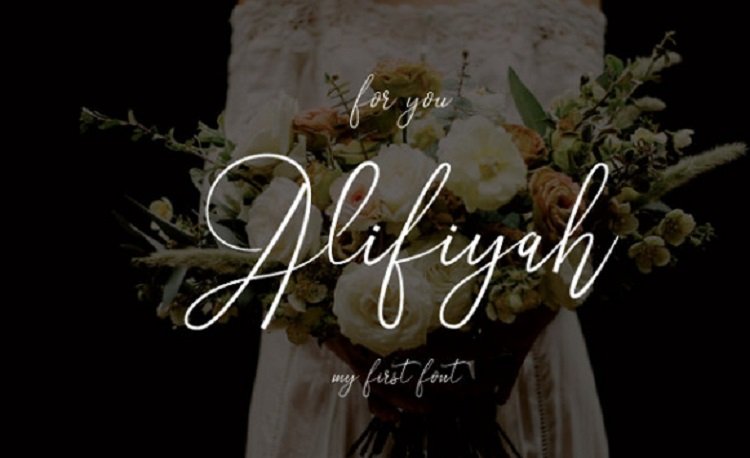
Alifiyah Handwritten Font
Alifiyah Handwritten Font berarti keindahan wanita.
Font ini terinspirasi oleh keindahan wanita dengan segala kelembutannya membuat font ini terlihat berkelas berkelas, elegan dengan lekukan yang lembut proyek Anda akan terlihat luar biasa dan menakjubkan.